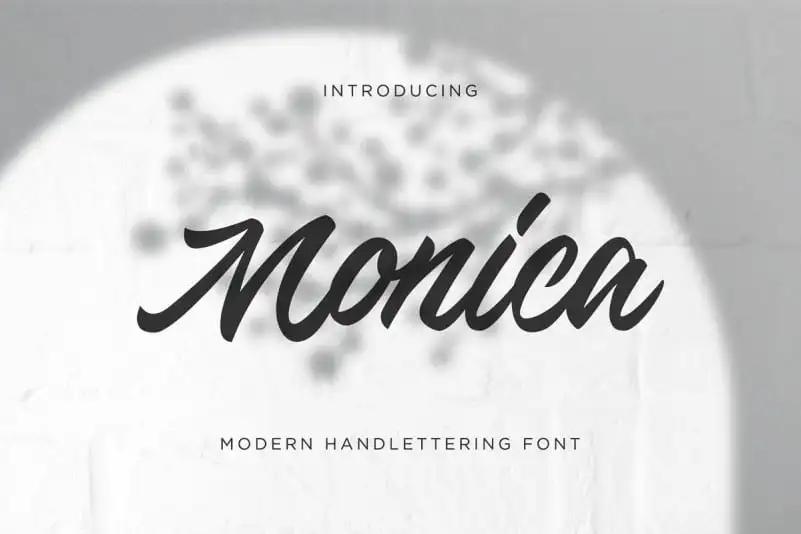
Monica Script Font – Download Grátis
A Monica Script Font é uma fonte criada com entusiasmo pela designer desplus. Ela leva seu design poderoso para um estilo elegante e sofisticado, incorporando características delicadas que dão a impressões de elegância e classe à qualquer projeto. Esta fonte evoca a feminilidade em todas suas formas suaves, tornando-a perfeita para ambientes onde deseja transmitir sofisticação e requinte, como design gráfico, identidades corporativas ou publicações luxuosas. Com seu traço curveado levemente arredondado, você pode alcançar um resultado que é atraente e impressionante, tornando qualquer projeto uma verdadeira estrela no seu setor. A Monica Script Font não apenas traz beleza, mas também originalidade e sofisticação à sua arte digitais.